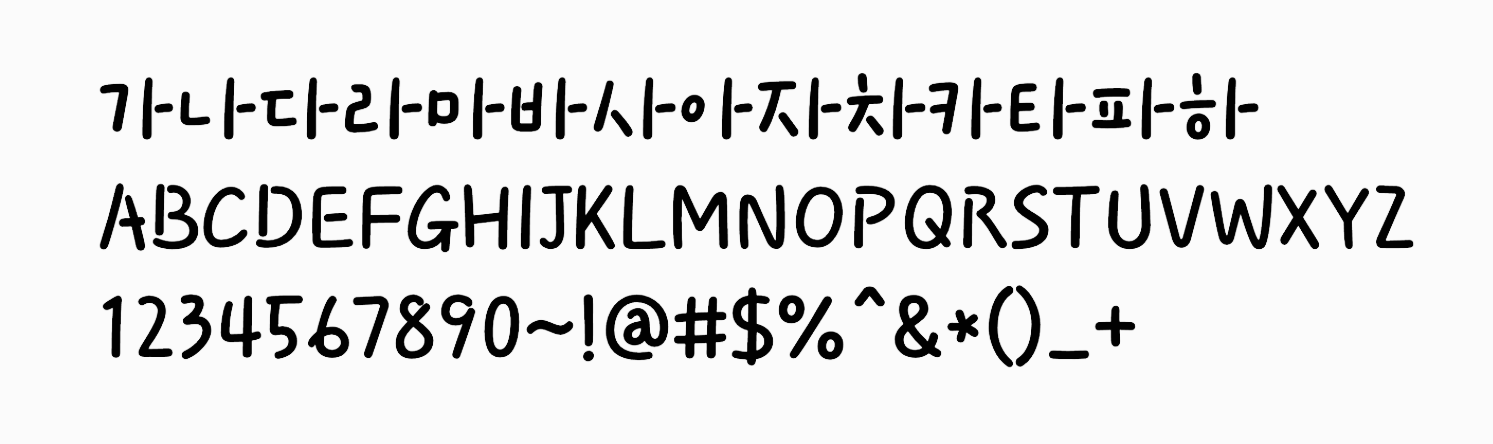
학교안심 칠판지우개
'학교안심 칠판지우개체'는 교육부와 17개 시도교육청, 한국교육학술정보원(KERIS)이 공동으로 국내 폰트 기업을 대상으로 공모를 통해 도입한 오픈 글꼴입니다. 이 폰트는 교육 현장에서 저작권 걱정 없이 자유롭게 활용할 수 있도록 개발되었습니다.
형태적 특징
이 글꼴은 칠판에 분필로 쓴 듯한 질감을 재현하여 따뜻하고 친근한 느낌을 줍니다. 글자의 획은 부드럽고 자연스러우며, 손글씨의 자유로운 흐름을 담고 있어 교육 자료나 어린이 대상 콘텐츠에 적합합니다. 특히, 오른쪽으로 곡선을 이루어 올라가는 가로획과 가로 중성의 사선 처리를 통해 동적인 느낌이 표현되어 경쾌함과 발랄한 인상을 줍니다.
활용 분야
'학교안심 칠판지우개체'는 다음과 같은 디자인 및 문서 작성에 활용하기 좋습니다:
- 교육 자료: 교과서, 학습지, 프레젠테이션 등 학생들을 위한 자료에 사용하면 학습 친화적인 분위기를 조성할 수 있습니다.
- 어린이 콘텐츠: 동화책, 어린이 잡지, 유아 교육 앱 등에서 활용하면 아이들의 흥미를 높이는 데 도움이 됩니다.
- 포스터 및 배너: 학교 행사나 캠페인 포스터, 배너 등에 사용하면 따뜻하고 친근한 이미지를 전달할 수 있습니다.